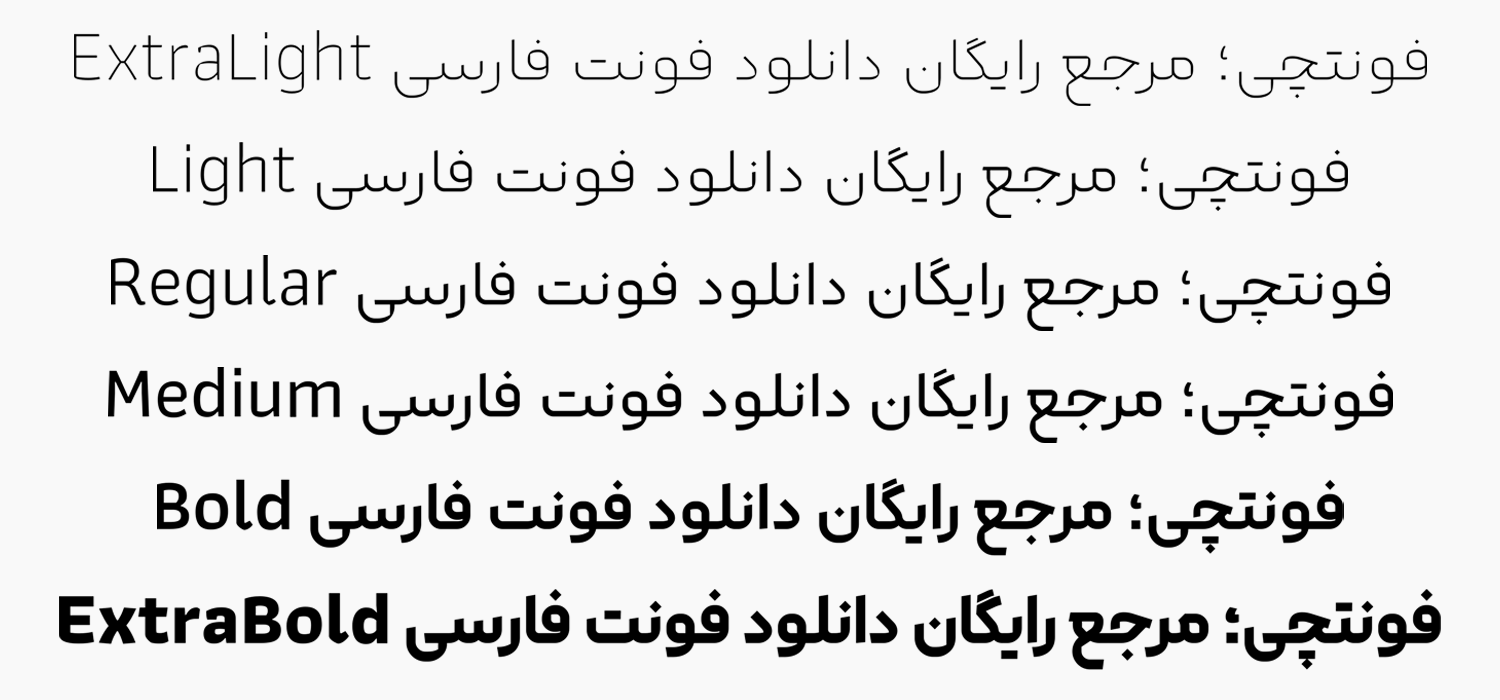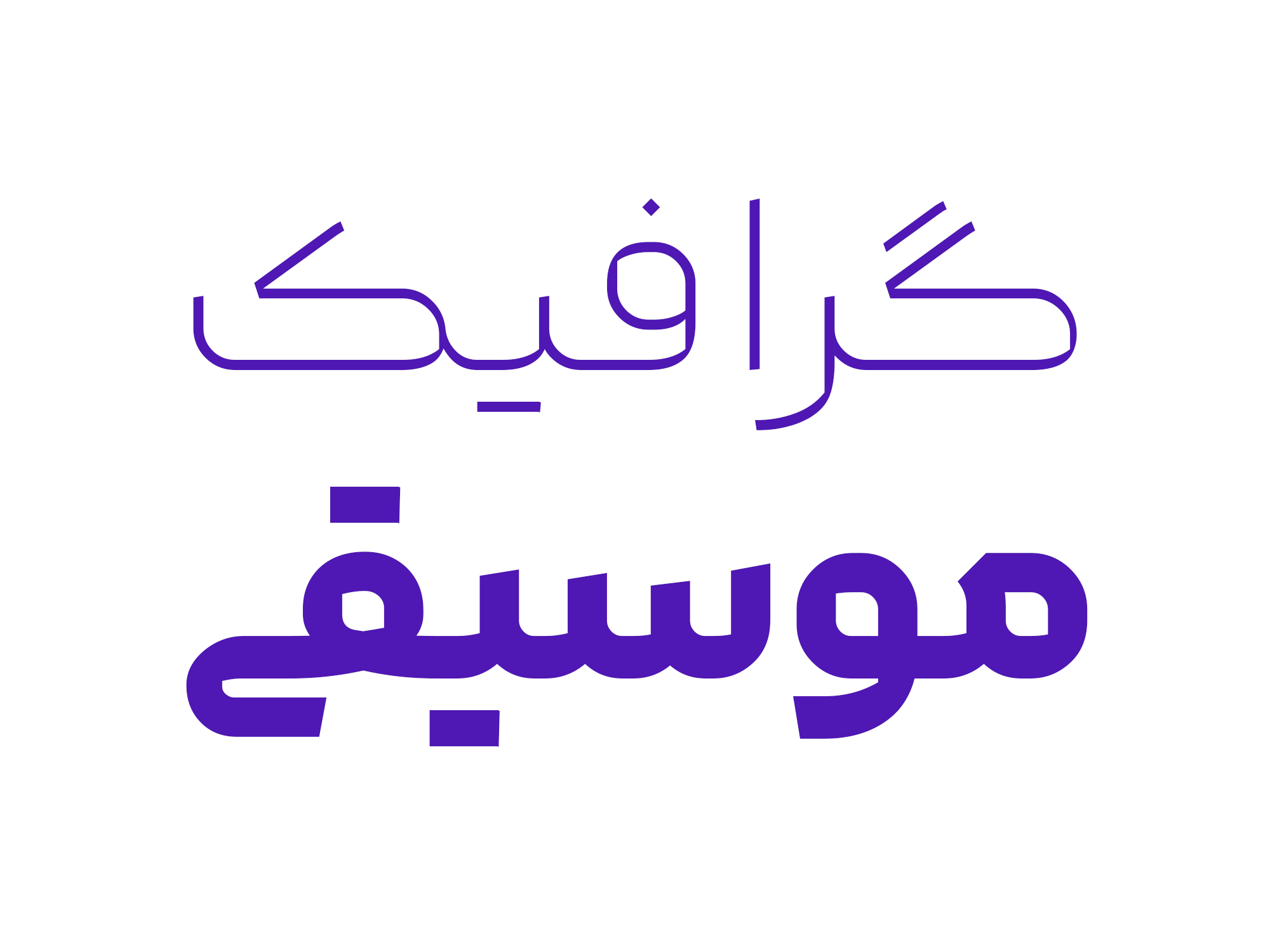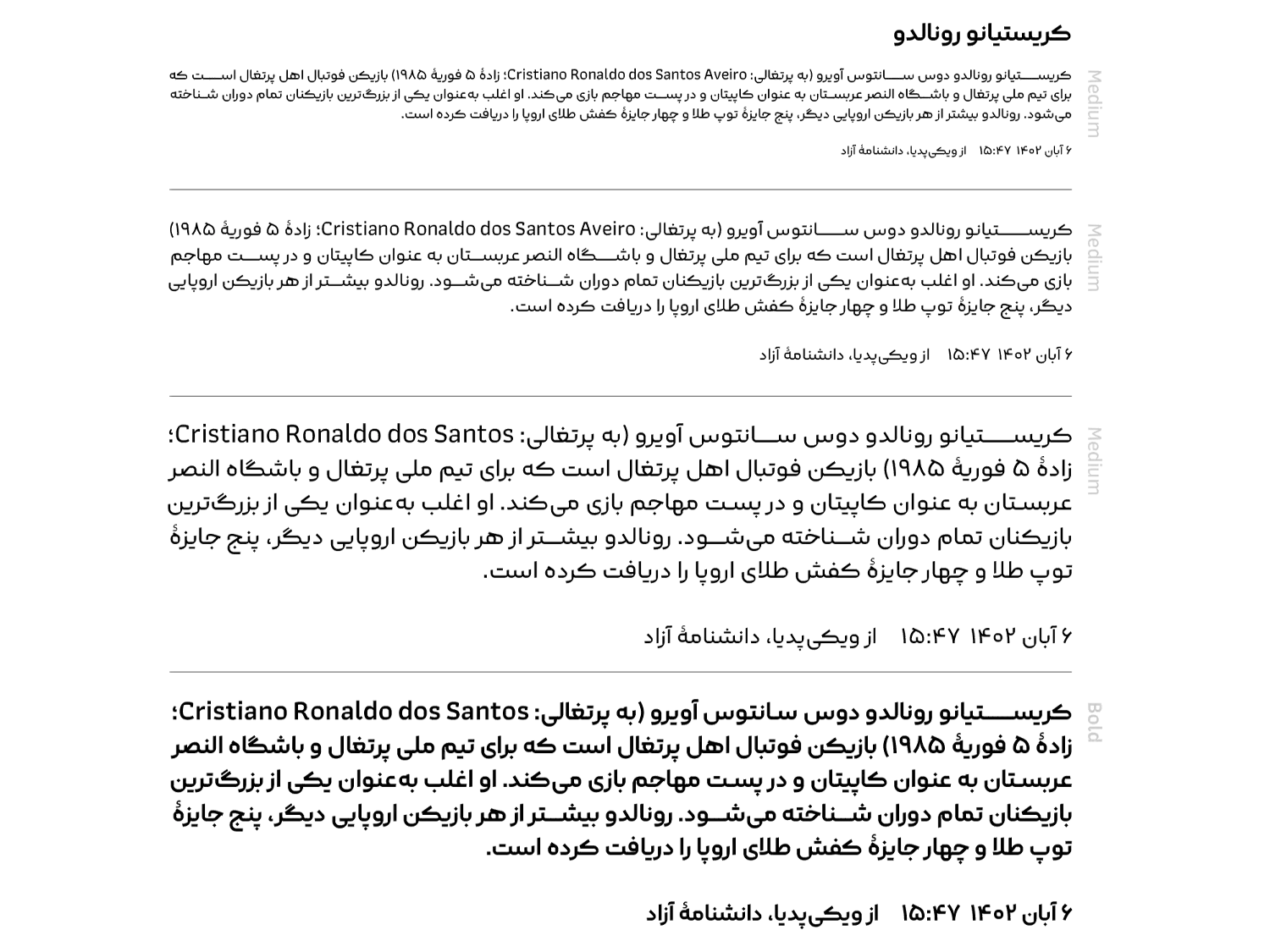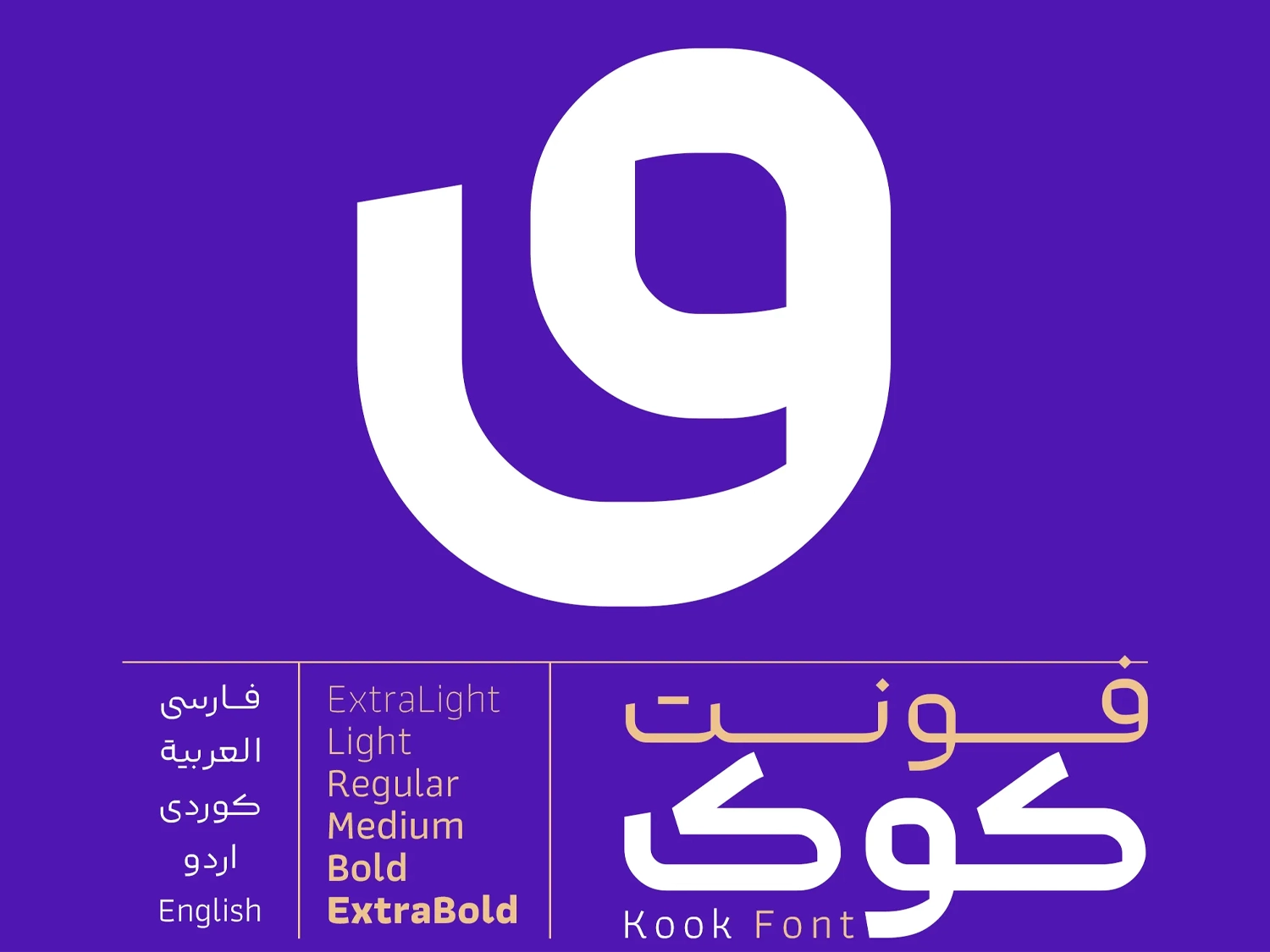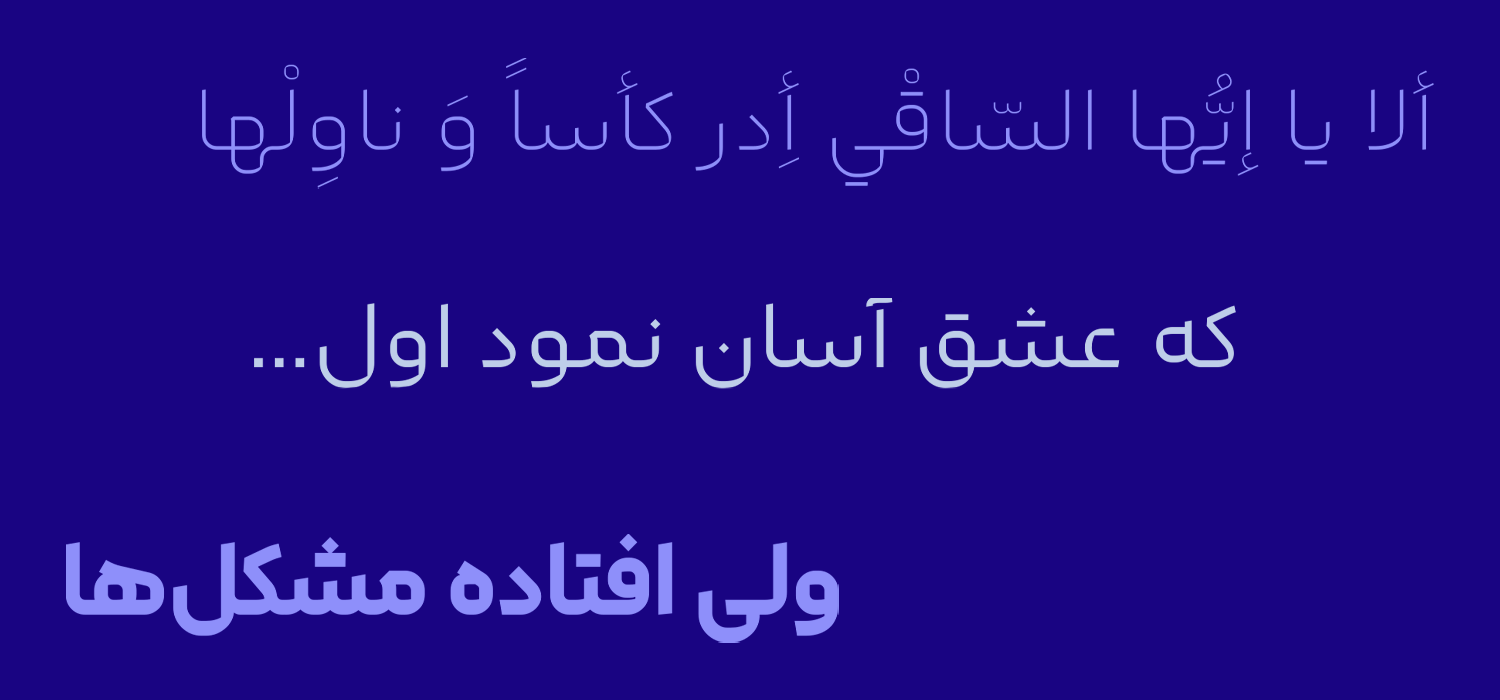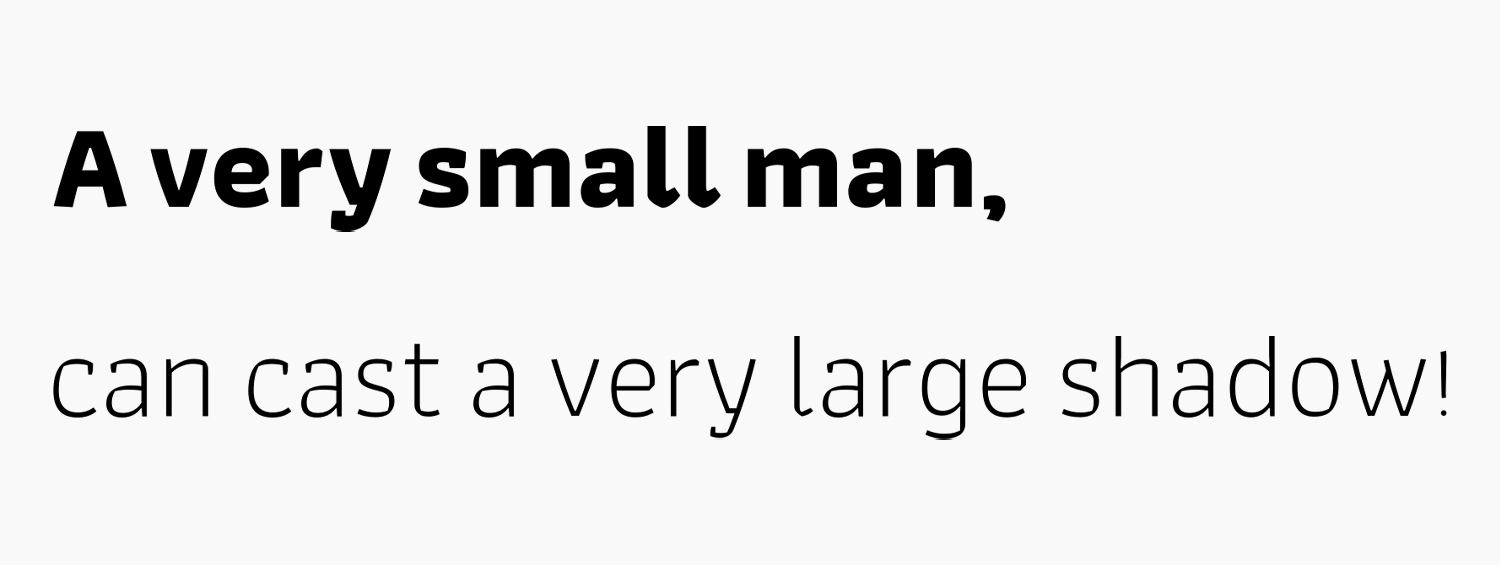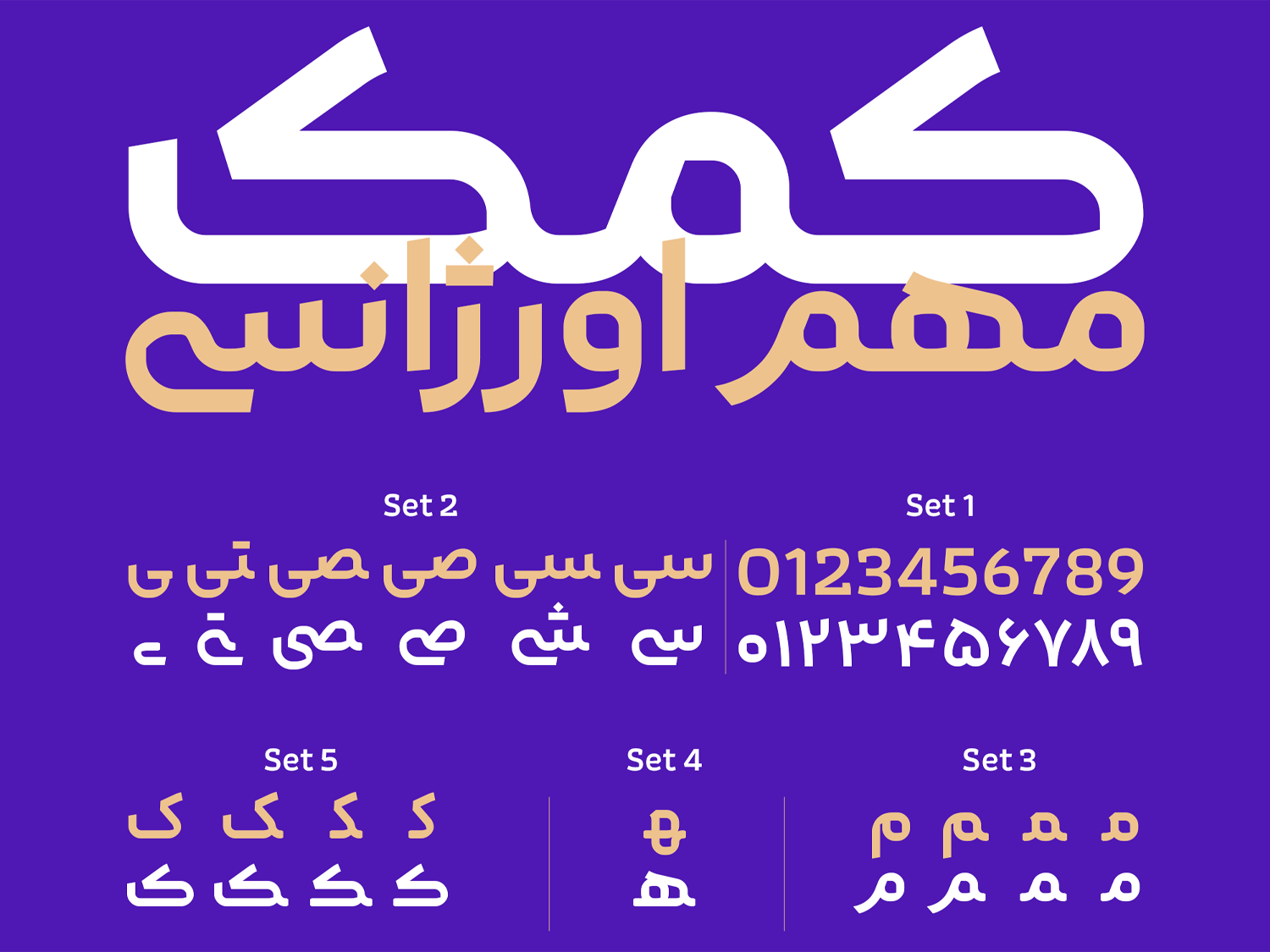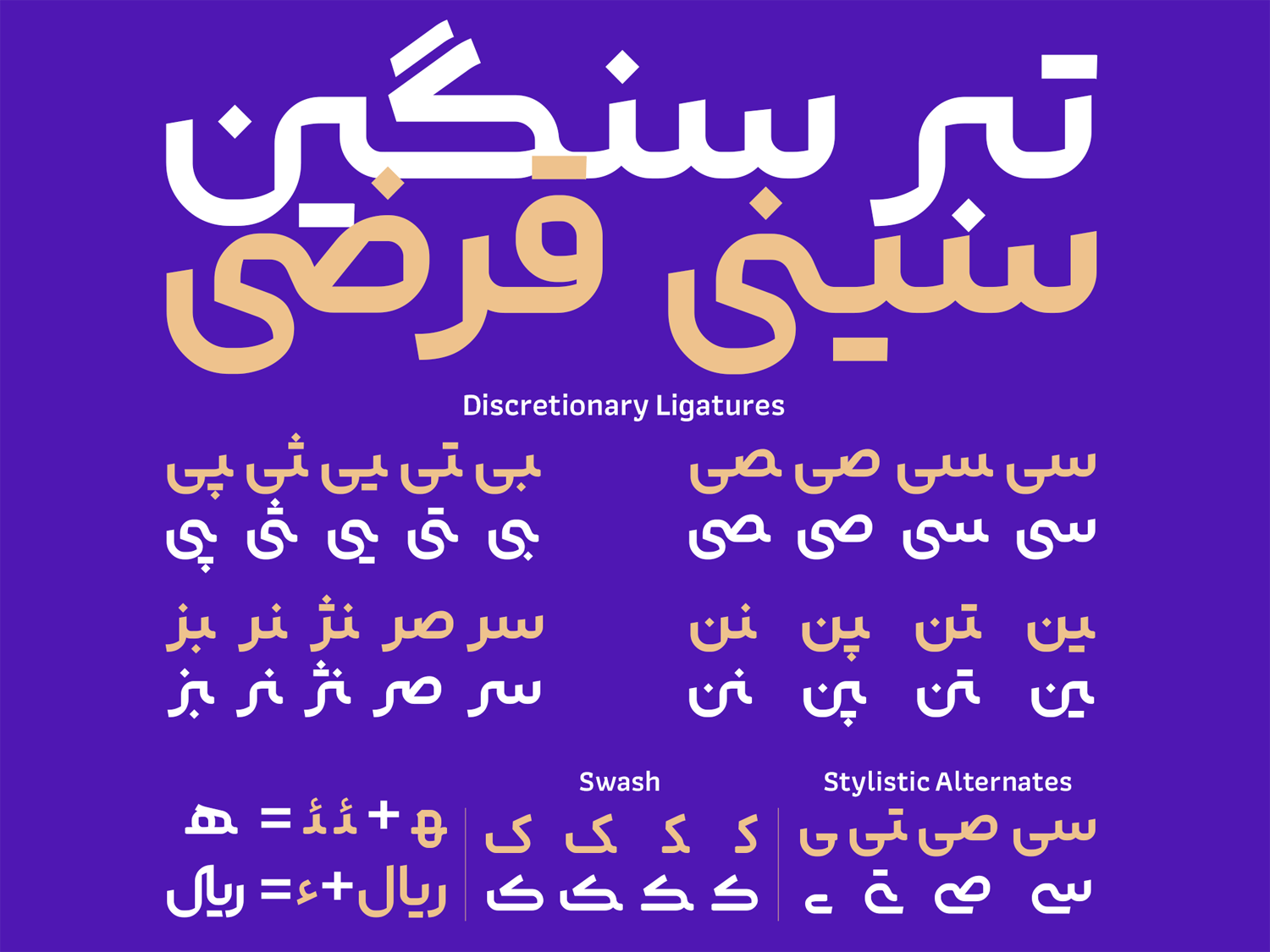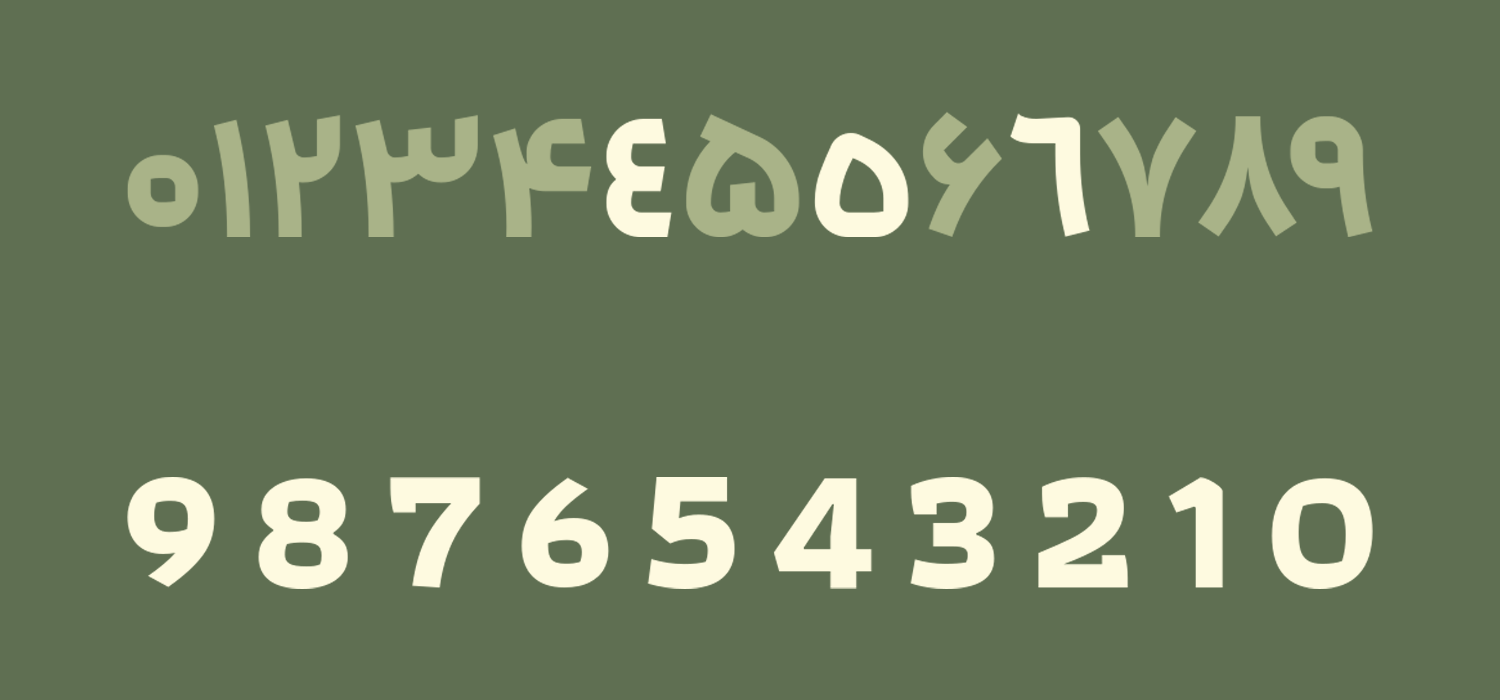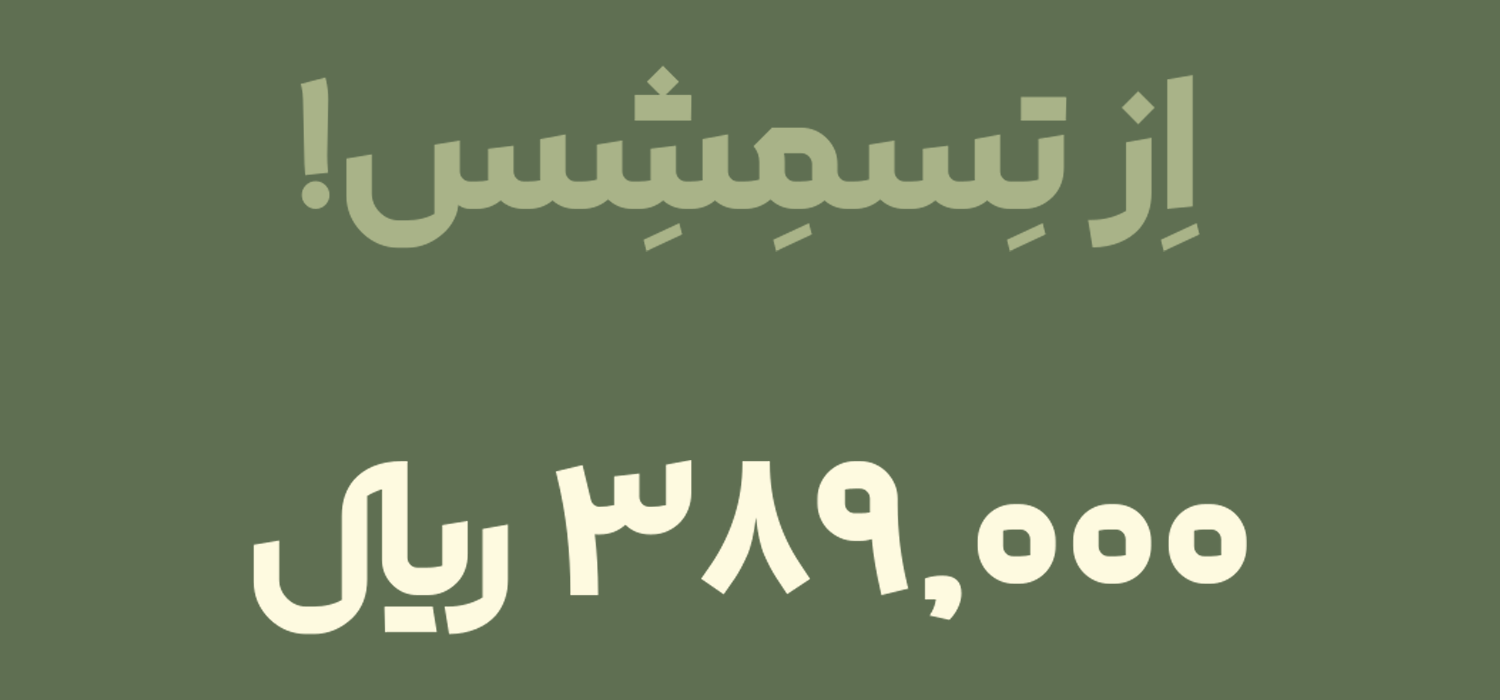
فونت کوک (Kook)
فونت کوک (به انگلیسی: Kook) جدید قلم سبک هندسی با تلفیق خوشنویسی است که برای استفاده در عناوین، تبلیغات و متونی که نیاز به یک فونت نمایشی داشته باشید کاربرد دارد. این فونت فارسی که نسبتا فانتزی هم بهنظر میرسد، برای استفاده رابط کاربری نیز مناسب است. فونت کوک رایگان نیست و با توجه به تنوع وزنی که دارد در دو بسته اقتصادی و حرفهای قابل خریداری است.
سعید حقیقت طراحی این فونت فارسی است که این قلم را با سبک هندسی، اما تلفیقی از خوشنویسی امروزی و معاصر درون آن ایجاد کرده است تا در بخشهایی همچون زوایا، چشمیها و منحنیها ظاهد یک ظرافت مثالزدنی از این قلم باشیم.
در ادامه این نوشته از سایت فونتچی به نقد و بررسی کامل فونت کوک خواهیم پرداخت؛ قلمی هندسی و نمایشی که برای استفاده در وب فونت و فونت موبایل میتواند روی ایجاد یک رابط کاربری یکپارچه انتخاب خوبی باشد که با توجه به جدید بودن مورد توجه قرار خواهد گرفت.
بررسی و دانلود فونت کوک (Kook)
برشها در فونت kook کمی زاویهدار هستند و در بعضی مفصلها شکستگیها و زاوایایی که به فونت داده شده تند و از حد ایدهآل بالاتر است که آن را به یک فونت جوان و معاصر تبدیل میکند. خمیدگیها گاها خارج از قاعده هستند که همه این ویژگیها این قلم را به فونتی ظریف، روان و در عینحال غیرسکون تبدیل میکند.
با اینکه این فونت از وزنهای متعددی همچون معمولی Regular پشتیبانی میکند؛ اما شاید برای استفاده در متون خیلی بلند ایدهآل نباشد. بهترین حالتی که این فونت از خود برجای میگذارد برای کارهای گرافیکی، تبلیغاتی، طراحی پوستر در شبکههای اجتماعی و عناوین است.
سبک طراحی و وزن فونت کوک فارسی
فونت کوک با اینکه جوان است؛ اما ساختاری ظریف دارد که در منحنیها و زوایا خود را بهنمایش میگذارد. چشمیهای فونت با ترکیبی از مربع با زوایای گرد بسیار نرم و زوایای تیز طراحی شده است که این فونت را جدی نشان میدهد.
ایده طراحی فونت زمانی به ذهنم رسید که در حال طراحی یک پوستر تبلیغاتی بودم. خواستار فونتی بودم که تلفیقی از خطوط هندسی و خوشنویسی باشد و همچنین همنشینی خوبی با فونتهای لاتین داشته باشد.
سعید حقیقت؛ طراح قلم کوک.
این فونت در ابتدا دارای ساختاری ساده و صرفا هندسی داشت. به مرور زمان استایلهای پیچشی و در کنار آن دادن زاویه به حروف روی آن اعمال شد تا هم قلم دارای ساختار نمایشی باشد و هم اینکه ظریف و معاصر بهنظر برسد.
این قلم از ۶ وزن مختلف شامل خیای نازک، نازک، معمولی، متوسط، بولد و خیلی بولد پشتیبانی میکند. با توجه به این تنوع وزنی از این قلم میتوان برای طراحی رابط کاربری و همچنین سبط ظریفی که دارد برای لوگوتایپ استفاده کرد.
شاید تنها کاستی که فعلا در این خانواده فونت وجود دارد عدم پشتیبانی از نسخه وریبل باشد که انتظار میرود در آپدیتهای آتی به آن افزوده شود.
پشتیبانی از ۵ زبان متنوع خاورمیانه ای و لاتین
فونت فارسی کوک محدود به این زبان نیست. زبانهای عربی، کردی و اردو به لطف رسم خط فارسی بودن از این قلم نیز پشتیبانی میکنند. همانطور که میدانید سایر قلمهای خاورمیانهای دارای حروفی هستند که نسبت به فارسی دارای ساختاری متفاوت یا کاملا دگرگون شده است.
برای نمونه حروف «ک، ی، ه، ؤ، ئ» در زبان عربی یا حروف «ﮧ، ﮩ، ے» در اردو که نسبت به فارسی کاملا متفاوت هستند. این قلم برای اینگونه حروف در سایر زبانها دارای گلیف اختصاصی است تا بر اساس استاندارد بینالمللی یونیکد بتوانید از هر گلیف متناسب با زبان خود استفاده کنید.
اعراب در این فونت با همنشینی مناسبی نسبت به سایر کاراکترهای «همزه، تشدید، سکون» در کنار هم قرار گرفته و ساختار فونت را ضمن نظم بخشیدن جدی خواهند کرد. اعراب در تمامی زبانها در فاصله درستی قرار گرفته و به حروف مجاور نخواهند چسبید.
همچنین برای زبانهای اردو و کردی که استفاده از کاراکترهای تزئینی و طرهها رایج است علاوه بر اعراب در این فونت پیادهسازی شده است.
فونت kook انگلیسی با همان سبک طراحی که حروف دارای زوایای کم، تغییر وزن حروف در زوایا و گاها تغییرات ناگهانی منحنیها هستند، با وام گرفتن از فونت اپنسورس Athiti پیادهسازی شده است تا کاملا متناسب با استایل و سبک فارسی باشد. با استفاده از این فونت که سبک هندسی و خوشنویسی را در خود دارد، دیگر برای زبانهای لاتین نیاز به تغییر قلم نخواهید داشت.
دارای ترکیبات و حروف جایگزین متنوع
ویژگی دیگر فونت کوک رایگان پشتیبانی از ساختارهای مختلف برای برخی حروف و ترکیبات است. با اینکه این قلم هنوز از نسخه وریبل پشتیبانی نمیکند، اما میتوانید ترکیبات و حروف متنوع زیادی را در شکلهای مختلفی تایپ کنید.
بهعنوان نمونه همانطور که در تصویر زیر میبینید، حرو و ترکیبات «ک، م، ـهـ، ـه، سی، شی، ضی، سی، تی» دارای اشکال مختلفی هستند که خصوصا در وزنهای سنگینتر ساختار قلم را نمایشیتر نشان خواهند داد.
یا در نمونه دیگری که مشابه تصویر زیر میبینید ترکیباتی نظیر «ـبی، ـتی، ـیی، ـثی، ـپی، ـین، ـتن، ـپن، ـنن، سر، صر، ـنژ، ـنر، ـبز» نیز دارای امکان تایپ متفاوت هستند.
این ترکیبات امکان تایپ متفاوت کلمات را به شما خواهند داد. در کاربردهای تبلیغاتی این ترکیبات تایپ متفاوت کلمات را در اختیار قرار میدهند که موجب نمایشیتر شدن کلمات کلیدی و افزایش جلب توجه مخاطب خواهد شد.